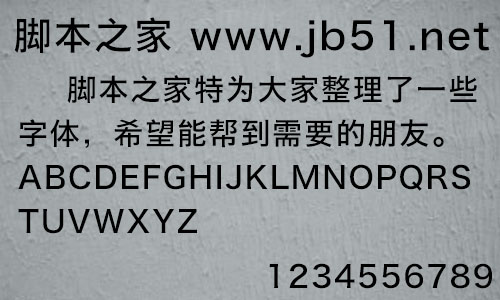
冬青黑體簡體中文W5是一款十分不錯的中文字體,這款字體筆觸粗細(xì)適中,端莊大氣,適合應(yīng)用于藝術(shù)設(shè)計(jì)、平面宣傳設(shè)計(jì)、網(wǎng)頁設(shè)計(jì)、書法字帖,海報(bào)設(shè)計(jì)等領(lǐng)域,需要的朋友不妨前來本站下載使用。